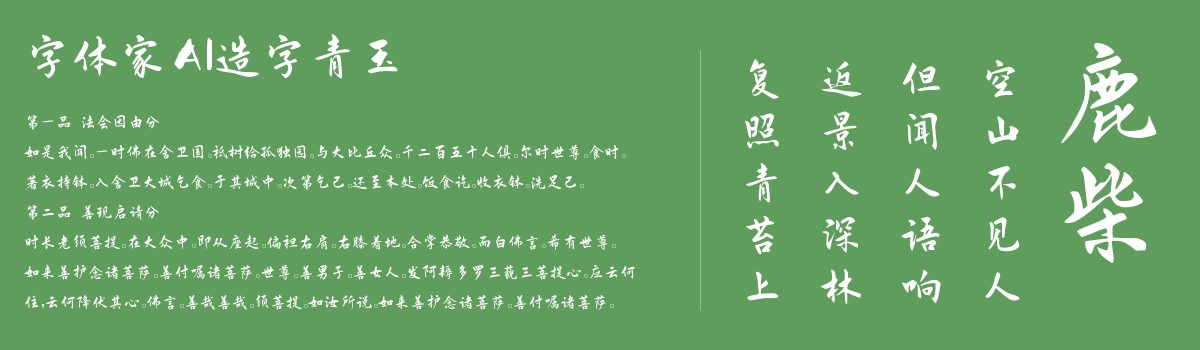
字体家AI造字青玉
字体家AI造字青玉是一款由字体家AI神笔造字生成的一款书法字体,这是一款手写风格字体,笔画兼具提按变化,粗细对比自然。起笔收笔多带书写惯性的轻顿或露锋,转折处圆转流畅,无生硬折角。字形结构舒展,部件搭配疏密有致,保留手写的自然灵动。线条偶有轻微牵丝,增强书写连贯性,整体兼具笔墨的温润质感与书写的洒脱气韵。比较适合用于艺术类装饰文字,海报、网页、广告设计,室内装饰,平面标题设计、食品包装、品牌标志等。